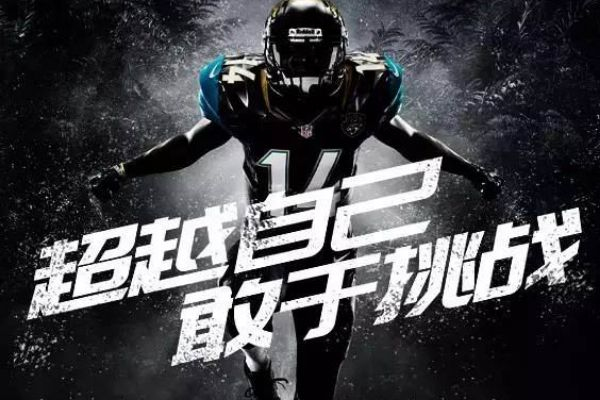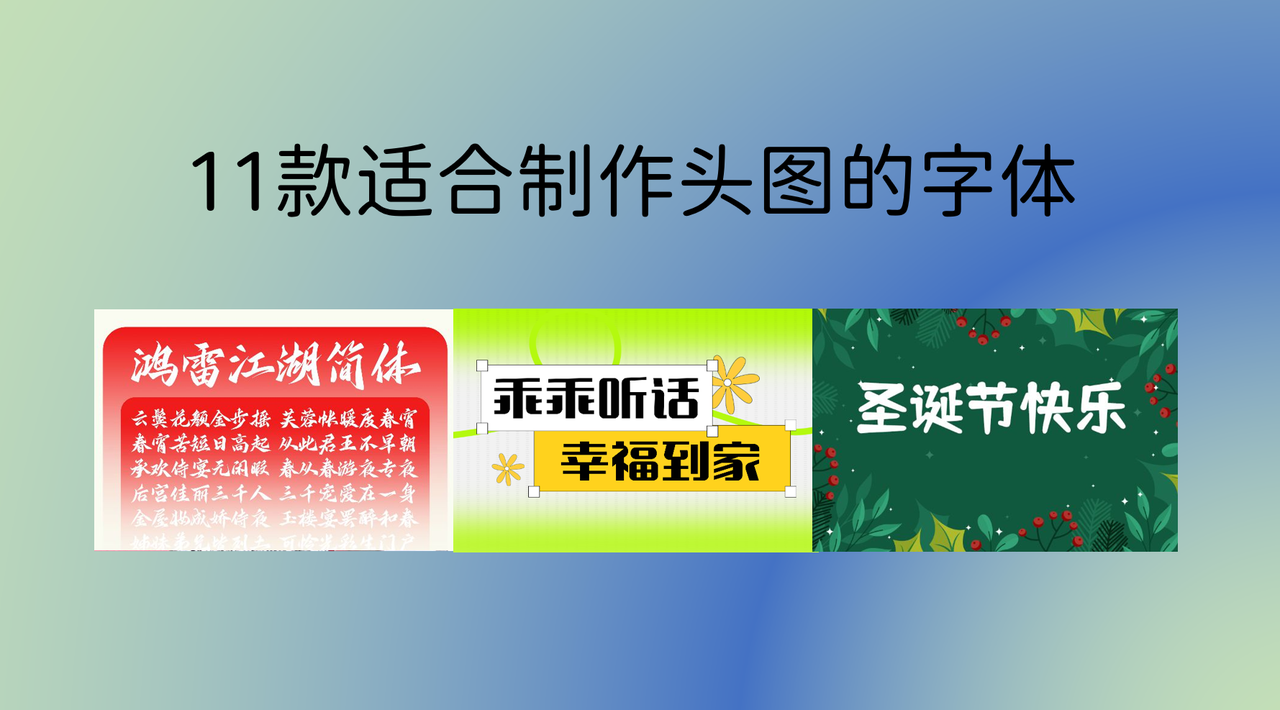
公众号封面没点击?11款适合制作公众号头图的字体推荐
公众号头图是文章的第一视觉,而字体是最重要的元素,如果字体选得不对,哪怕背景图再漂亮,也很难提升点击率。本文分享 15 款适合制作公众号头图的字体给你,涵盖了各种风格。换上这些字体,你的封面不仅能告别平庸,还能让你的运营工作变得更轻松、更有成就感。
演示佛系体
演示佛系体的笔画粗细非常随意,看起来像是用毛笔随手写就的,带有一种手写的温度和呼吸感。它不争不抢,却自带一种高级的疏离感。如果你想让读者看到封面就静下心来,这款字体是绝佳选择。
鸿雷江湖
鸿雷江湖笔画很有张力,墨迹边缘有一种自然的干枯效果,就像武侠小说里的江湖气息。它的视觉冲击力极强,能瞬间抓住读者的眼球。
郑庆科乖乖体
郑庆科乖乖体是我见过最萌、最治愈的字体之一。它的字形圆润,笔画结构像小孩子的涂鸦,虽然不正规,但显得特别真诚。它能给封面增添一种天然的亲和力,让人忍不住想靠近。
得意黑
得意黑是近年来爆火的一款开源字体。它有一个很特别的设计:带有一定的倾斜度,而且曲线非常饱满。这让它看起来既有力量感,又带有一种俏皮的幽默感,非常有辨识度。
适合用在时尚资讯、流行梗盘点或者是那种轻松活泼的短评封面。它能给画面增加一种灵动的感觉,不显死板。
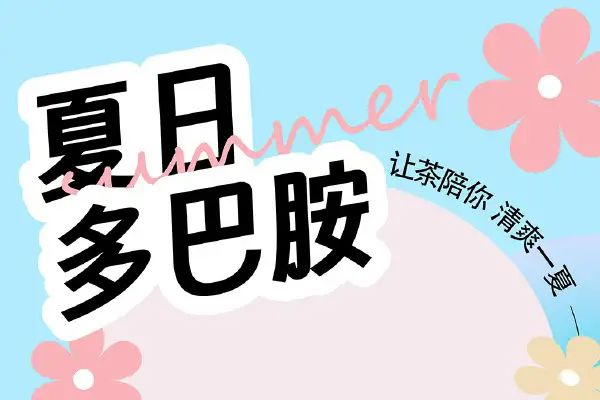
庞门正道标题体
这款字体就是为了“大标题”而生的。它的笔画极粗,视觉中心非常稳,有一种顶天立地的气势。它的结构非常紧凑,非常适合做那种字数不多的短标题。适合促销活动、爆款好物推荐或者是干货合集等场景。
站酷快乐体
站酷快乐体是一款让人看了心情会变好的字体。它的笔画粗细不一,结构歪歪扭扭,充满了童趣和欢乐。它没有正经字体的束缚感,非常自由。
适用场景:节日问候、线下团建或者是那种分享快乐瞬间的推文。
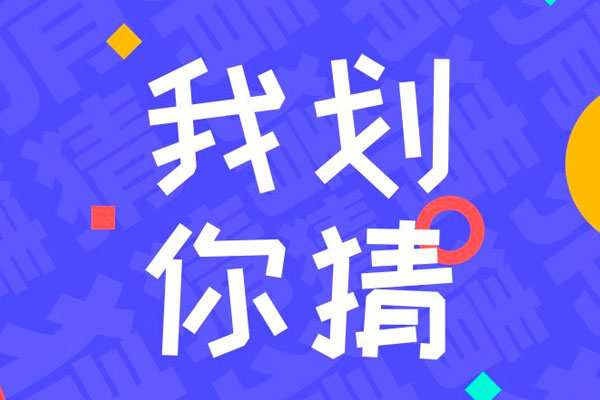
抖音美好体
抖音美好体的设计融合了动态感和现代审美,笔画末端处理得非常圆滑,带有一种年轻人的朝气和快节奏的美感。
它能让封面看起来很有“活力”。适合短视频运营秘籍、潮流趋势报告或者是年轻人感兴趣的话题。
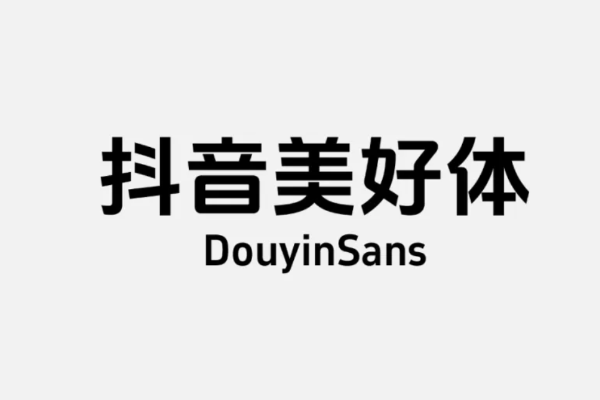
优设标题黑
优设标题黑的斜切角处理得非常巧妙,既有黑体的沉稳,又有艺术字体的灵感。它的字重非常适合做主标题,沉稳中带着一点灵动。
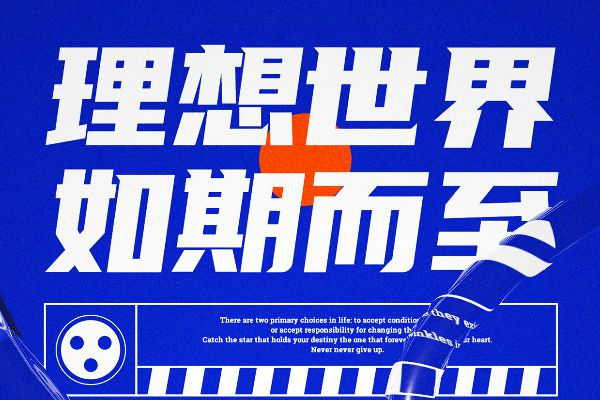
仓耳舒圆体
仓耳舒圆体的线条全部由圆滑的曲线构成,没有一个硬角。这种字体给人的视觉感受非常柔软、舒适,就像是棉花糖或者是清晨的阳光。它能给读者提供一种情绪上的抚慰,增加内容的亲和力。
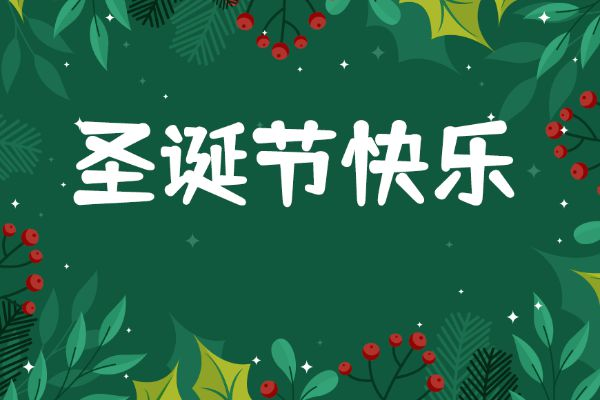
霞鹜文楷
这款字体完美融合了楷书的韵味和黑体的简洁。它不像传统楷书那么复杂,也不像黑体那么冰冷。它读起来非常清晰,带有一种淡淡的书卷气,非常有亲和力。
适用场景:走心的小众推荐、个人心路历程分享或者是书单推荐。
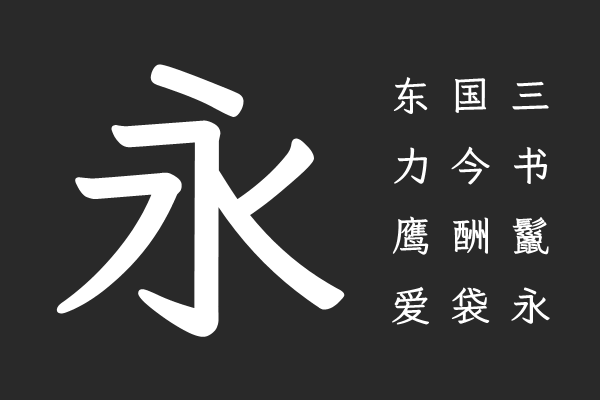
站酷庆科黄油体
站酷庆科黄油体带有一种强烈的复古感,笔画粗壮但转角圆润。这让它看起来像极了 80 年代的广告牌字体,很有复古潮流的感觉。
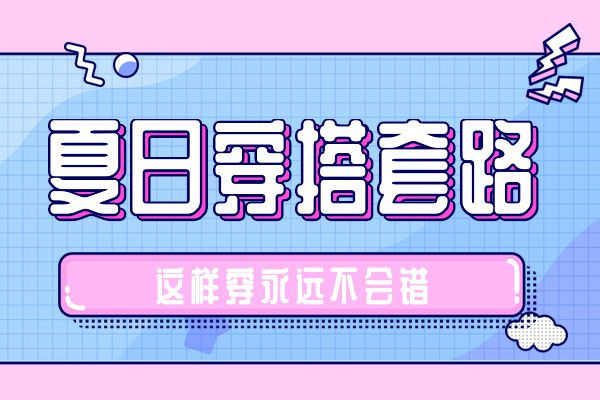
设计公众号头图的几个实操心得
字数不要太多
头图的空间有限,在手机上显示时尺寸更小。我通常建议主标题控制在 10 个字以内。如果标题太长,读者的视觉焦点就会涣散。你可以选一款像“庞门正道标题体”这样有冲击力的字体做主标题,再选一款“阿里巴巴普惠体”较细的版本做副标题,形成视觉上的层级感。
颜色反差要大
如果背景图颜色很杂,你可以给字体加一个半透明的色块底衬,或者给字体加一个浅浅的阴影。这样能保证无论背景怎么变,文字都能被清晰读出来。我曾经因为字体颜色和背景太接近,导致那一期的点击率直接掉了一半,这个教训非常深刻
记得留白
不要把字体塞满整个画面,给边缘留出一点呼吸的空间。这就像装修房子一样,家具摆得太满会让人感到压抑。适当的留白能让字体更有质感,也能让读者的注意力更集中在文字本身。